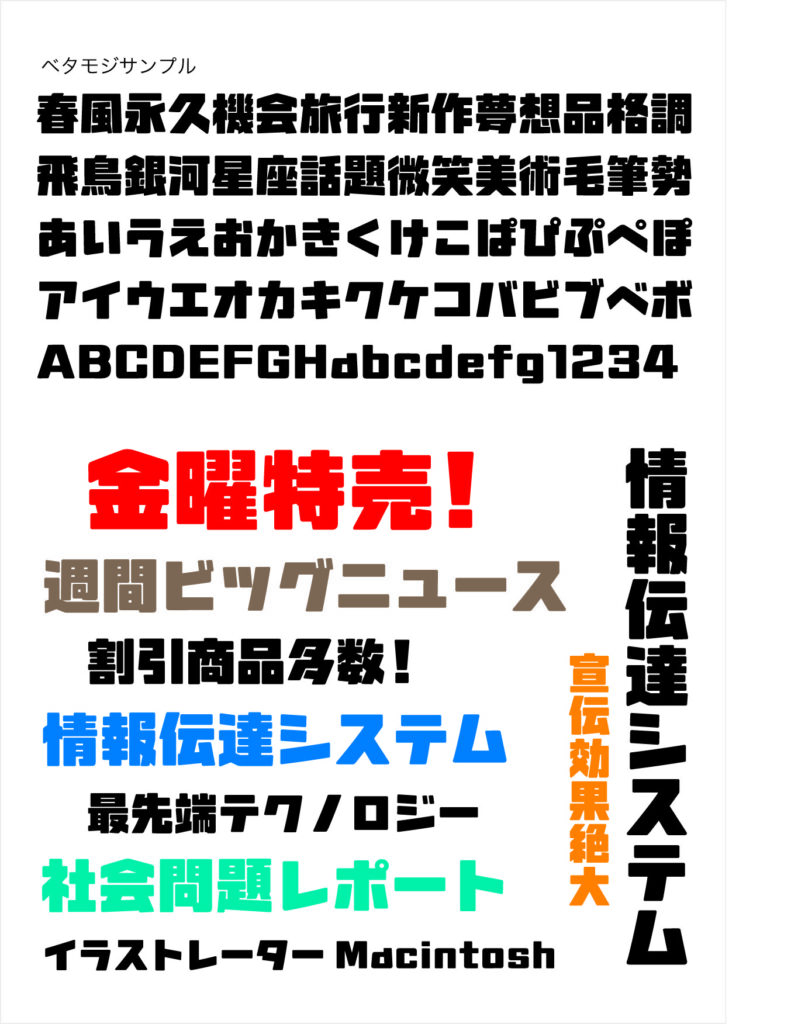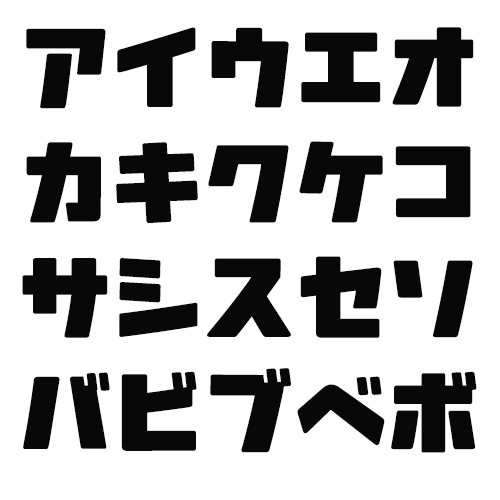
この度、Open Typeフォント [ べタモジ ] を発売しました。極太文字です。チラシなどの見出し用として作りました。直線文字ですが、線の角を少し丸めて柔らかさを出しました。 購入はこちらから↓ べタモジ べタモジ ¥ 5,000(税込)送料及び代引き手数料無料 Open Typeフォント [ べタモジ ] を発売しました。極太文字です。チラシなどの見出し用として作りました。直線… 中村書体室 文字サンプル